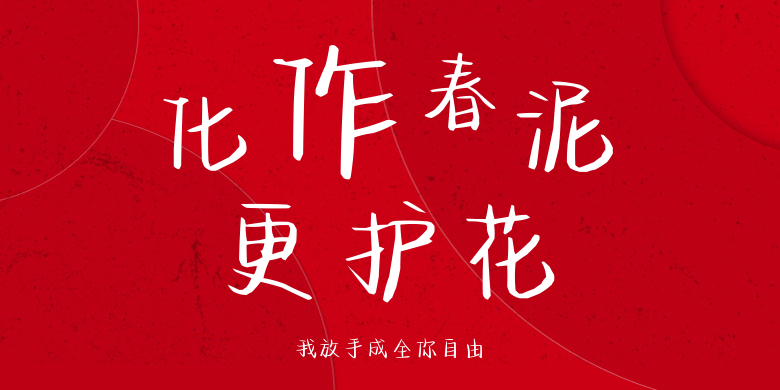
我放手成全你自由
我放手成全你自由,这款字体结构工整、笔画清晰,兼顾美观与易读性,适用于标题、正文、海报、包装、LOGO 等多种场景。字形优雅稳定,风格百搭耐看,适配日常排版与创意设计,让文字呈现更舒适、更具质感。我放手成全你自由一笔一画,皆是细节,以均衡的比例、流畅的线条打造舒适视觉体验,字形端正大气,风格简约现代。无论是商业设计、品牌宣传还是日常排版,都能轻松驾驭,让文字更有格调与力量。我放手成全你自由字体下载。